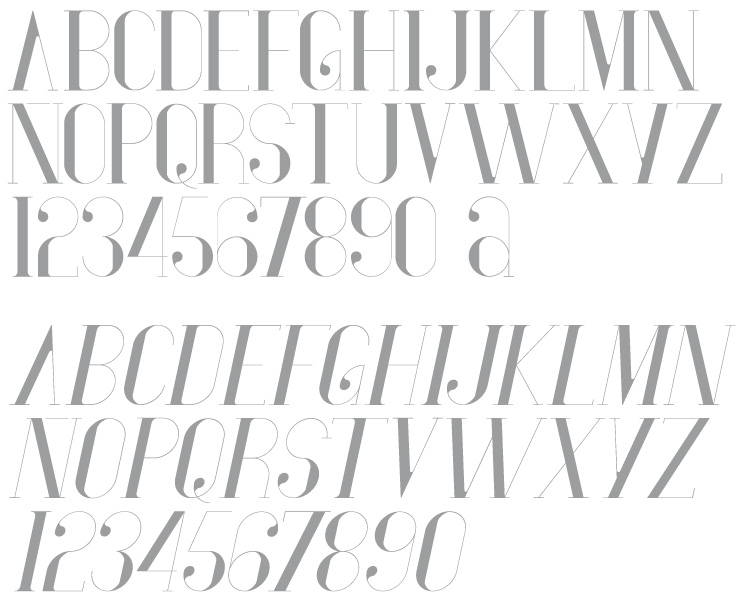
Una tipografía ligera, femenina y con aires a Didot o Bodoni.
Creada por Anthony Neil Dart, un diseñador multidisciplinar de Sudáfrica que reside en Seattle.